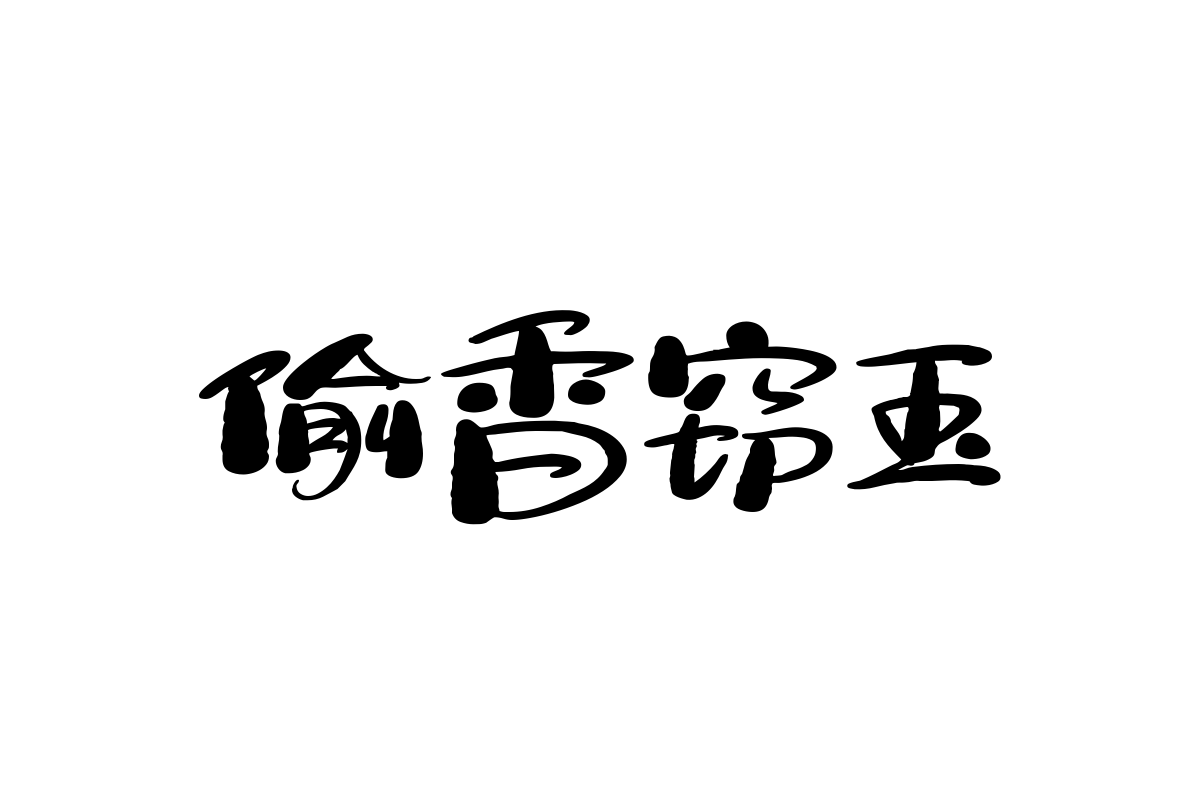
汉仪小松冰淇淋是一款具有现代感的中文字体,它以其圆润、柔和的字形和独特的风格而受到广泛的喜爱。这款字体适用于各种需要强调温馨、舒适感觉的场合,如广告宣传、产品包装、书籍封面等。
字体特点:
1. 字形圆润:汉仪小松冰淇淋的字形设计圆润饱满,给人一种温馨、舒适的视觉感受。
2. 线条流畅:字体中的笔画线条流畅自然,没有生硬的感觉,使得整体看起来更加和谐。
3. 风格独特:这款字体的设计独具匠心,既有现代感又不失传统韵味,适合各种风格的设计需求。
4. 适用范围广泛:无论是用于文字排版还是图形设计,汉仪小松冰淇淋都能展现出其独特的魅力,满足不同场景的需求。
总之,汉仪小松冰淇淋是一款非常实用的中文字体,它以其独特的设计风格和良好的视觉效果,为设计师提供了丰富的创意空间。